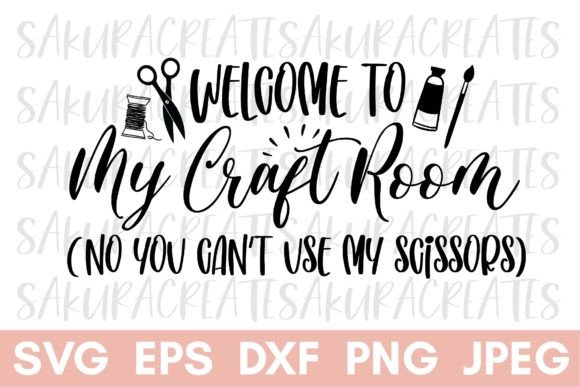
Crafting Quote Crafter Handmade Saying
Encontrar los elementos de diseño adecuados puede ser un desafío, pero Crafting Quote Crafter Handmade Saying ofrece una colección excepcional que eleva tu trabajo al instante.
Elaborado con precisión, Crafting Quote Crafter Handmade Saying proporciona vectores limpios, tipografía suave y una licencia comercial para tu tranquilidad.